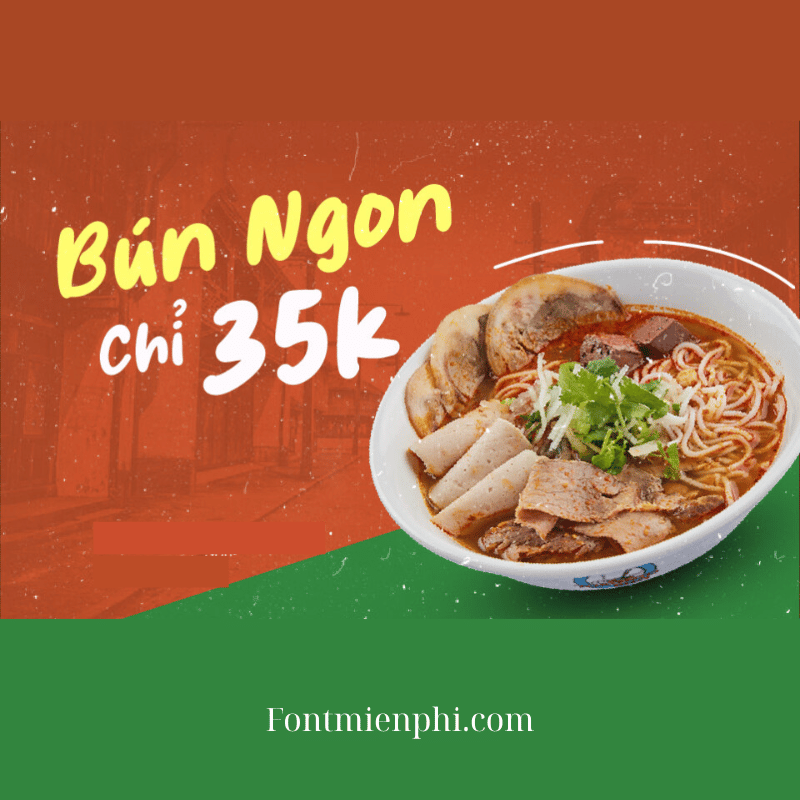
Font Việt hóa 1FTV VIP Freshco
Font Việt Hóa 1FTV VIP Freshco – Phong Cách Chữ Độc Đáo, Sáng Tạo
Giới Thiệu
Font Việt hóa 1FTV VIP Freshco là bộ font chữ độc quyền, thiết kế dành riêng cho ngôn ngữ Tiếng Việt. Với phong cách tươi mới, hiện đại, font chữ này phù hợp cho thiết kế đồ họa, in ấn, quảng cáo và các dự án sáng tạo. Được tối ưu hóa cho cả display và text, 1FTV VIP Freshco mang đến trải nghiệm đọc mượt mà, bắt mắt.
Đặc Điểm Nổi Bật
• Thiết kế độc đáo: Nét chữ sắc sảo, phá cách, phù hợp với xu hướng thiết kế 2024.
• Hỗ trợ Tiếng Việt đầy đủ: Bao gồm cả các ký tự có dấu, đảm bảo tính thẩm mỹ và chính xác.
• Đa dạng ứng dụng: Dùng cho logo, poster, banner, social media, bao bì sản phẩm.
Lợi Ích Khi Sử Dụng
• Tăng tính chuyên nghiệp cho ấn phẩm thiết kế.
• Tiết kiệm thời gian chỉnh sửa với bộ font chuẩn Việt hóa.
• Dễ dàng kết hợp với các font khác để tạo hiệu ứng đẹp mắt.
Kết Luận